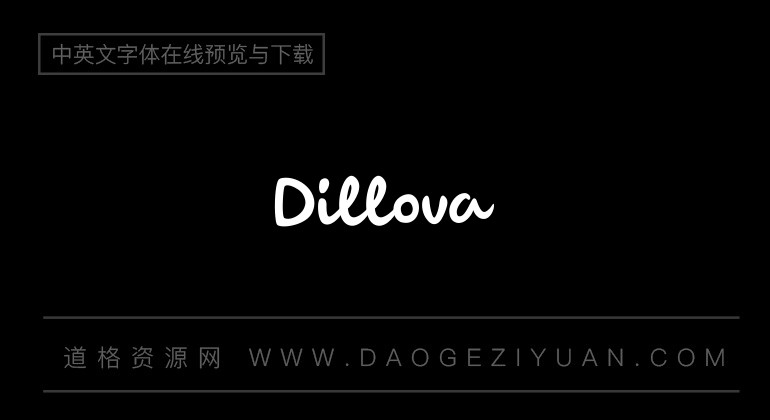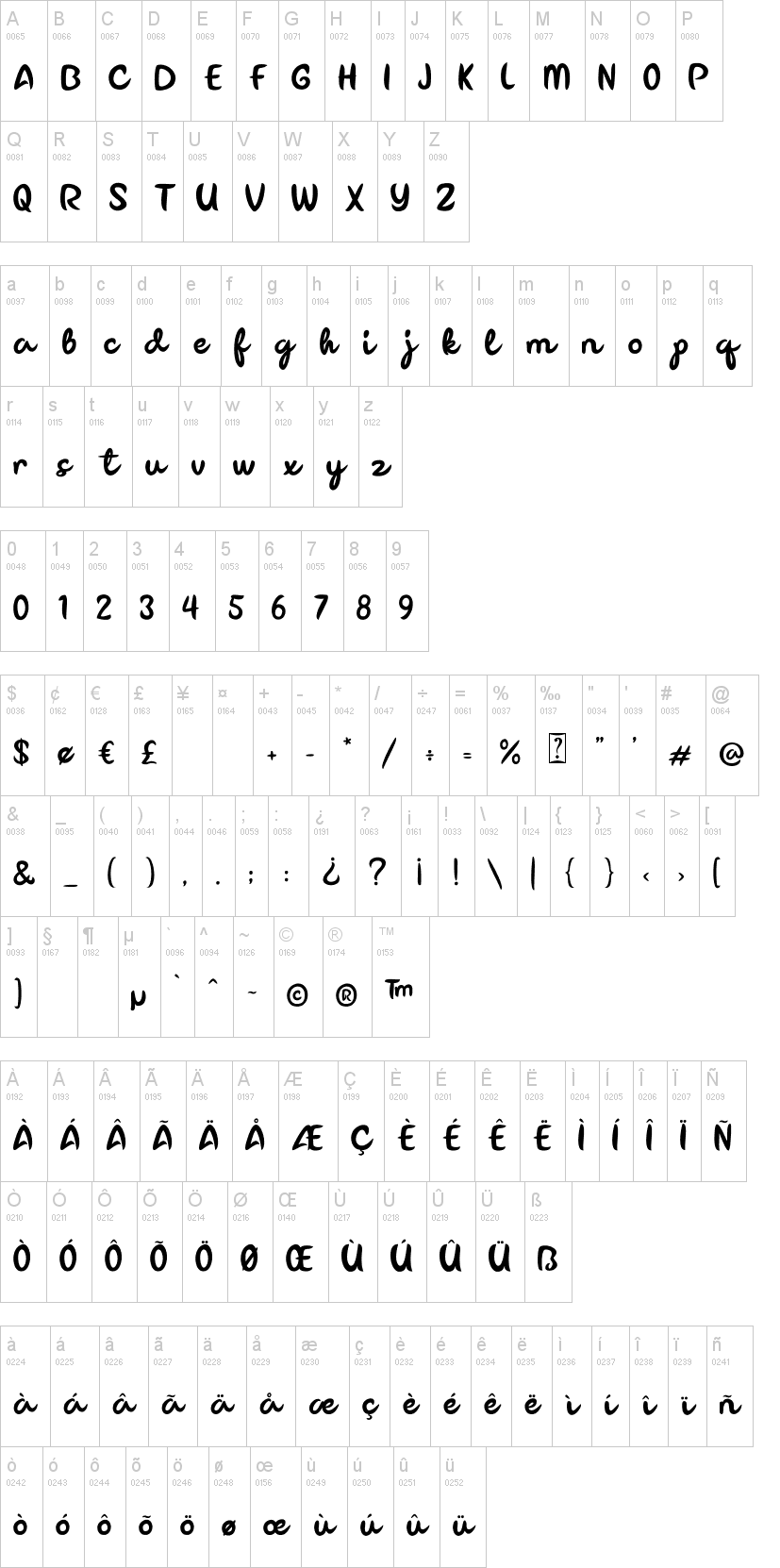
Dillova 是一款极简主义风格的字体,它具有简洁、明快、轻快的特点,适用于各种类型的设计项目,尤其是平面设计、网页设计、应用程序界面等。Dillova 字体的字体形状精细,笔画清晰,细节精致,使用它可以让设计师更容易地控制文字的外观。它还具有良好的可读性,可以清楚地传达设计项目的信息,并且可以让文本看起来更加有趣。内容介绍
Dillova是一款非常不错的手写艺术字体,具有很好的视觉感,适合于文化类的宣传设计、商业类品牌的广告和产品包装设计以及个性化文字排版等较多场景。